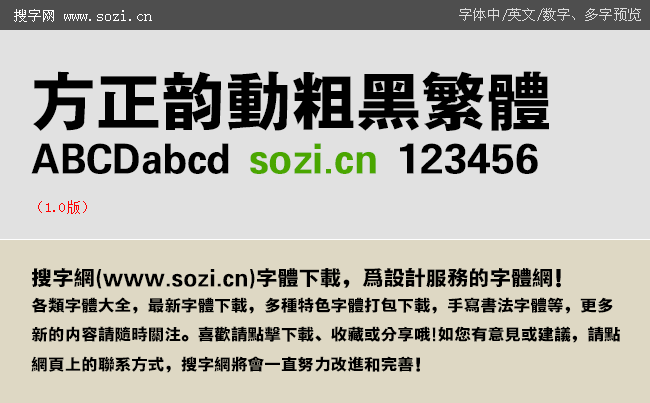
方正韻動粗黑繁體(FZYDCHFW)
搜字網(wǎng)提供一款方正韻動粗黑繁體中文字體下載,韻動黑去掉了原黑體筆畫上的喇叭口裝飾,使字體風格更加簡約時尚。在豎、撇、提的起筆處增加了裝飾頭,使字體更具個性。在撇、捺、點的設計上力求角度自然合理,不僅舒展有度,而且富有彈性和力度;豎鉤的長短適度,轉折靈活。對字面適當加以擴大,使字體更加莊重平穩(wěn),增強了版面的視覺沖擊力。適合書籍設計、展板設計、海報設計等廣告設計場合使用。